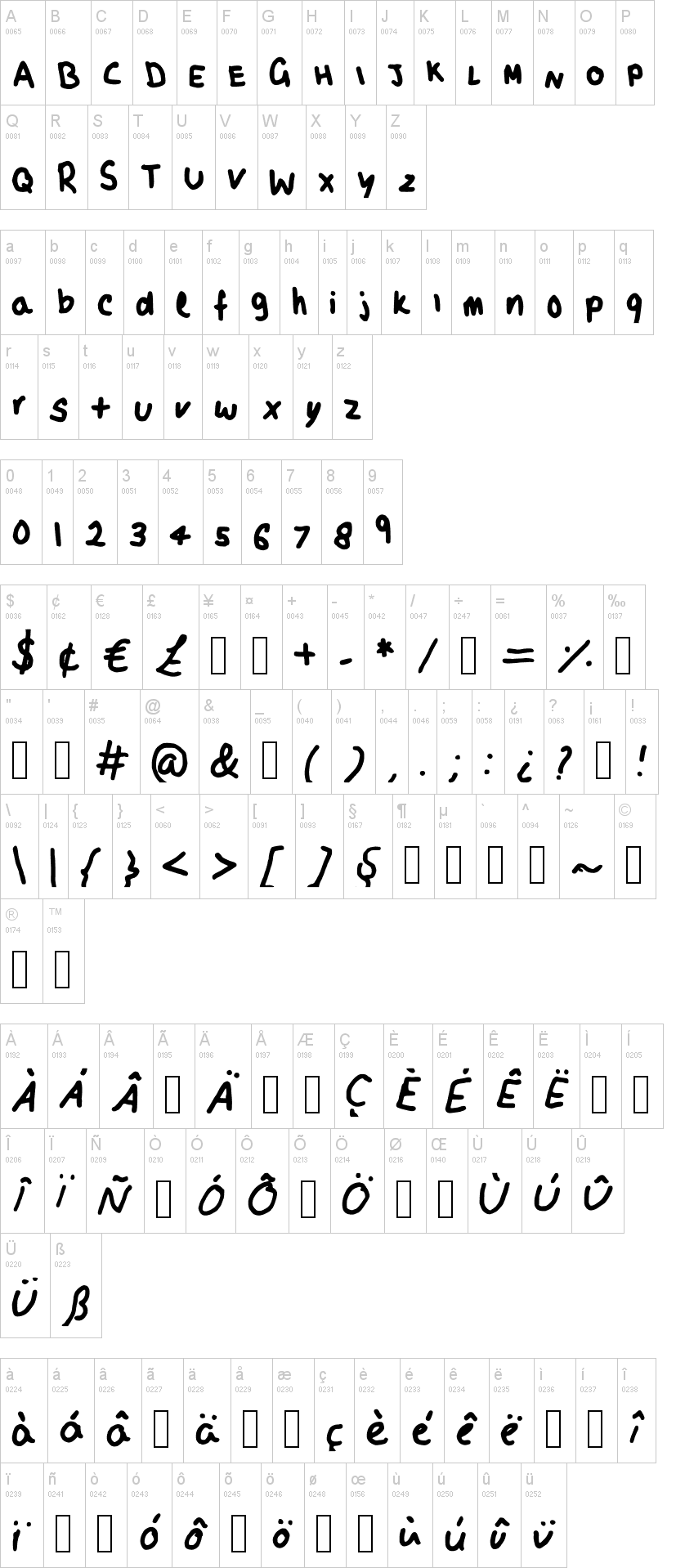
Mayas Script
Mayas Script 是一款由 Fontfabric 公司推出的手写体字体,它具有流畅的笔画,温柔的色彩,令人印象深刻的设计,适用于各种场合,包括海报,书籍,标志,标题,网页,T恤等。Mayas Script 字体具有非常强大的功能,可以帮助您轻松创建漂亮的图形,提供更多的选择,可以自定义字体,以及更多的文本效果,让您的作品更加精彩。
Mayas Script是一款非常不错的手写艺术字体,具有很好的视觉感,适合于文化类的宣传设计、商业类品牌的广告和产品包装设计以及个性化文字排版等较多场景。